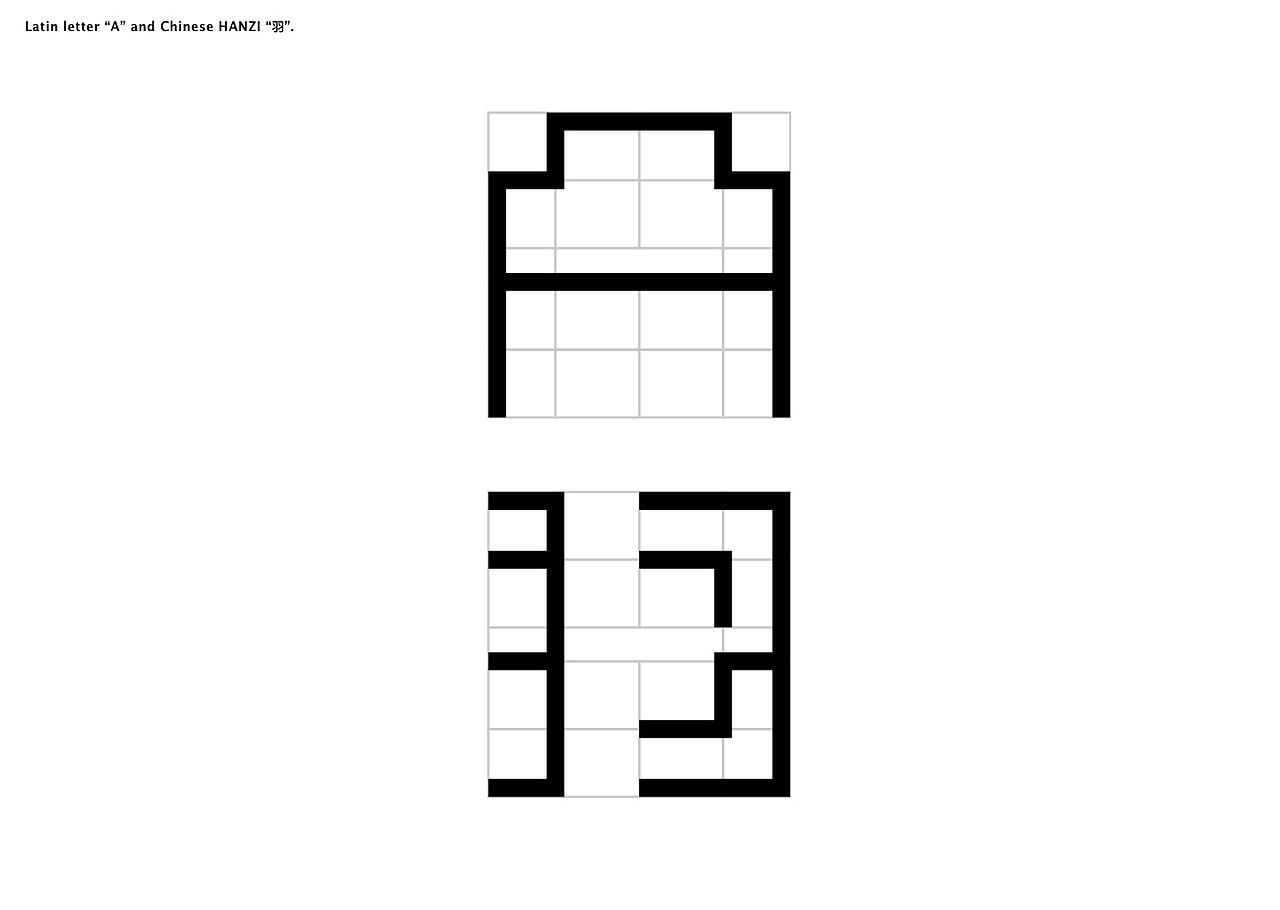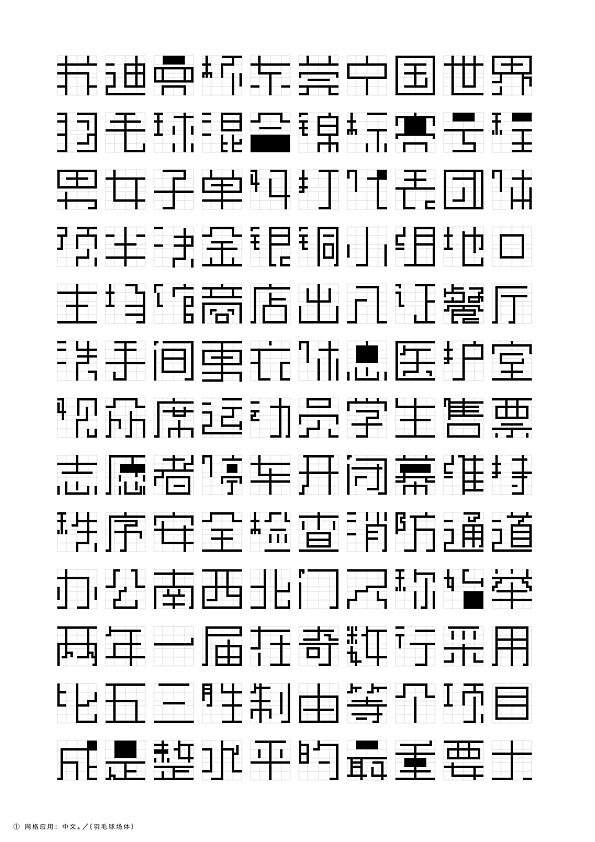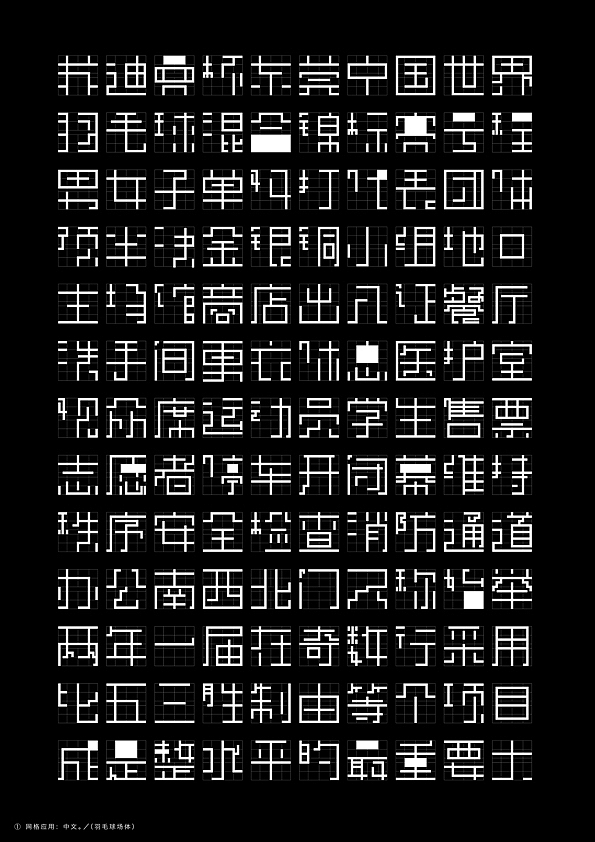
羽毛球场体|中英文字体实验
郭伟杰
这是一套实验字体, 目的是探索中英文同时基于相同网格的设计和排版的可能性。
我以两年前的个人参加苏迪曼杯羽毛球锦标赛VI设计竞赛的作品为起点,建立了一个
基于羽毛球场边线的网格, 并以此进行文字的设计。
我认为基于同一网格的字体能传达出一致的个性, 也许能为实践(品牌,展览等)提供一个新的可能。